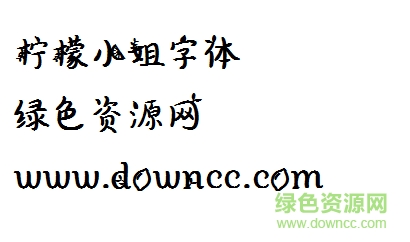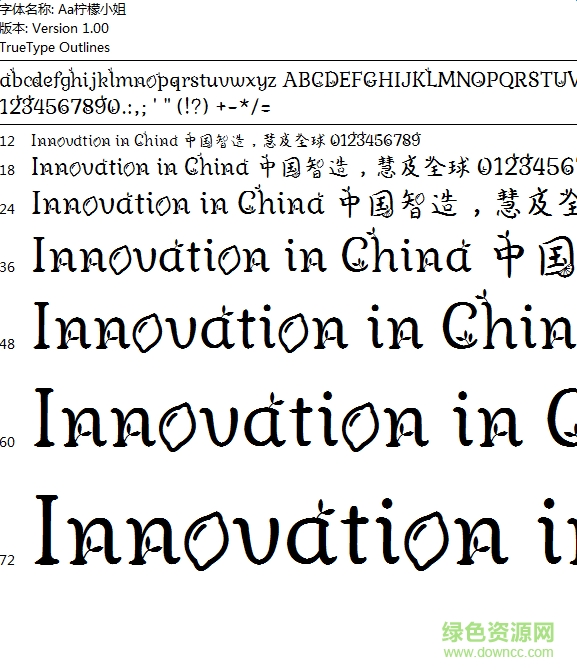
檸檬小姐字體是一款可愛(ài)的檸檬風(fēng)格字體軟件,字體帶檸檬圖案點(diǎn)綴,十分呆萌可愛(ài),運(yùn)用于文章書(shū)寫設(shè)計(jì)再合適不過(guò)了,更多好看的字體下載盡在綠色資源網(wǎng)!
檸檬小姐字體是一款可愛(ài)中文字體,該字體筆畫(huà)細(xì)膩,大字效果突出且引人注目;并且最大程度還原作者書(shū)寫字形,細(xì)節(jié)表現(xiàn)完整,且字庫(kù)完整,可以廣泛應(yīng)用于名片設(shè)計(jì)、新聞媒體、宣傳海報(bào)、ppt、影視制作以及內(nèi)容用字等領(lǐng)域。